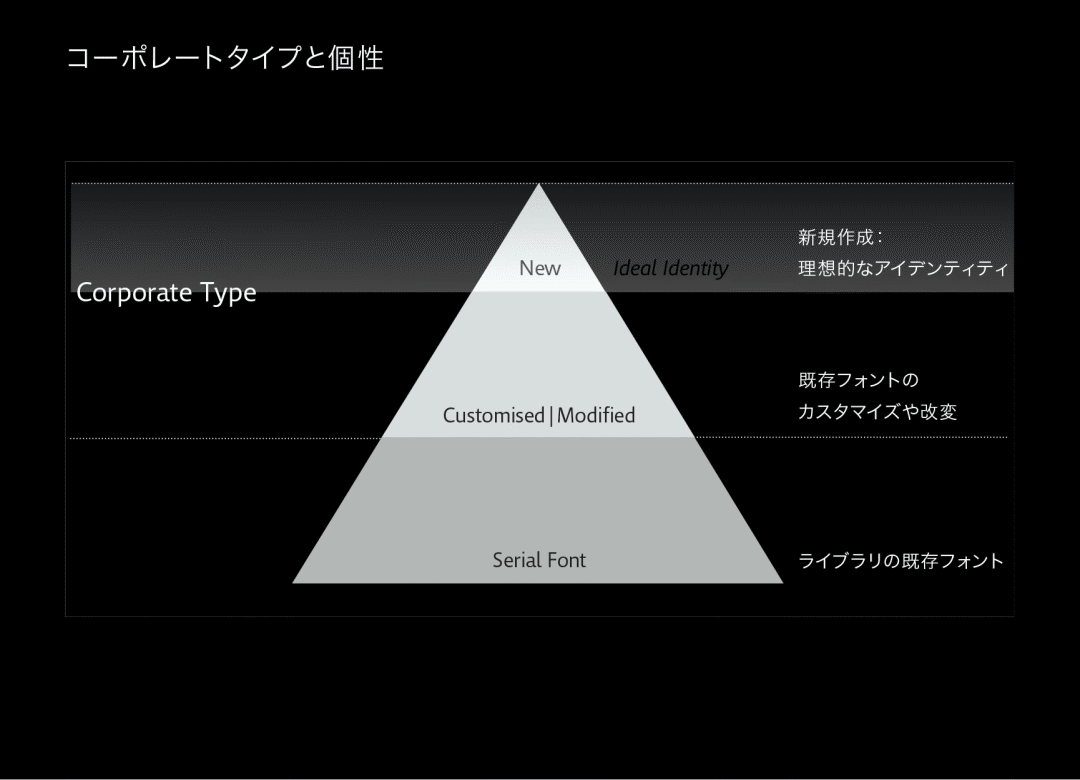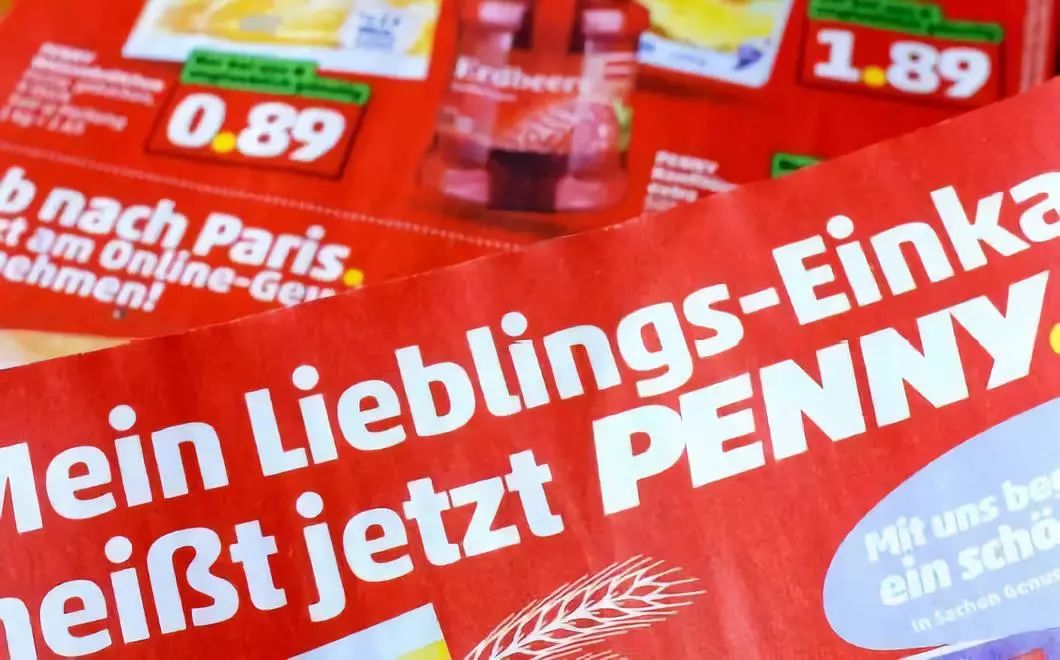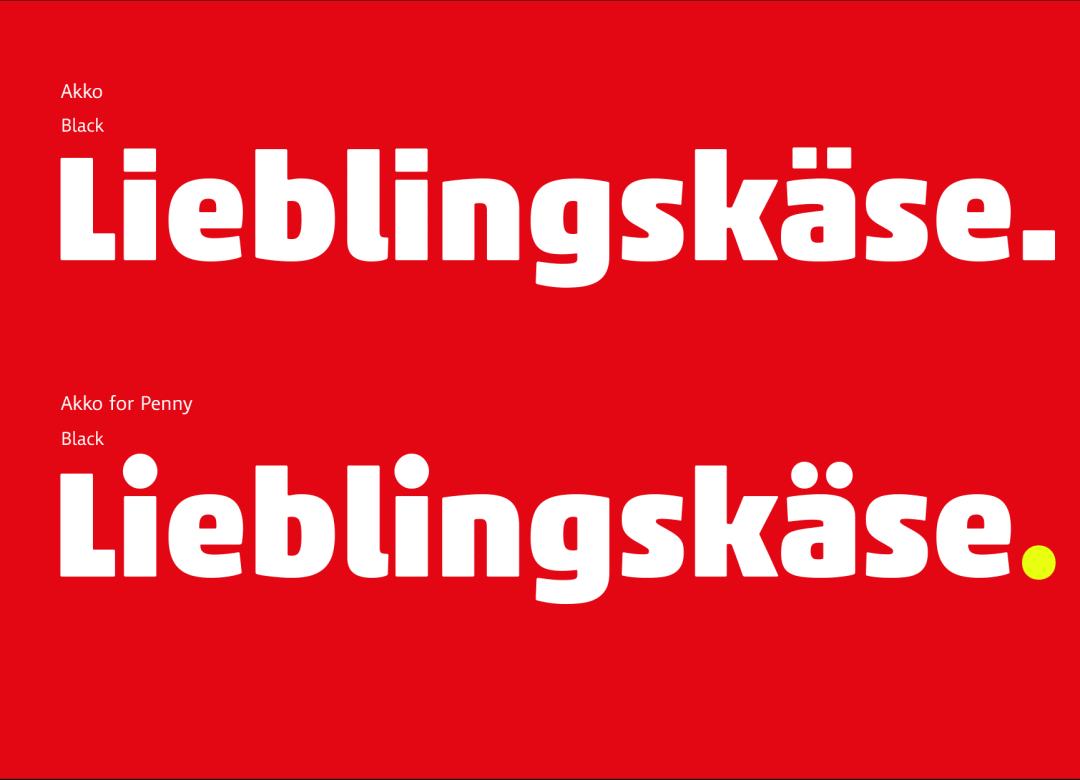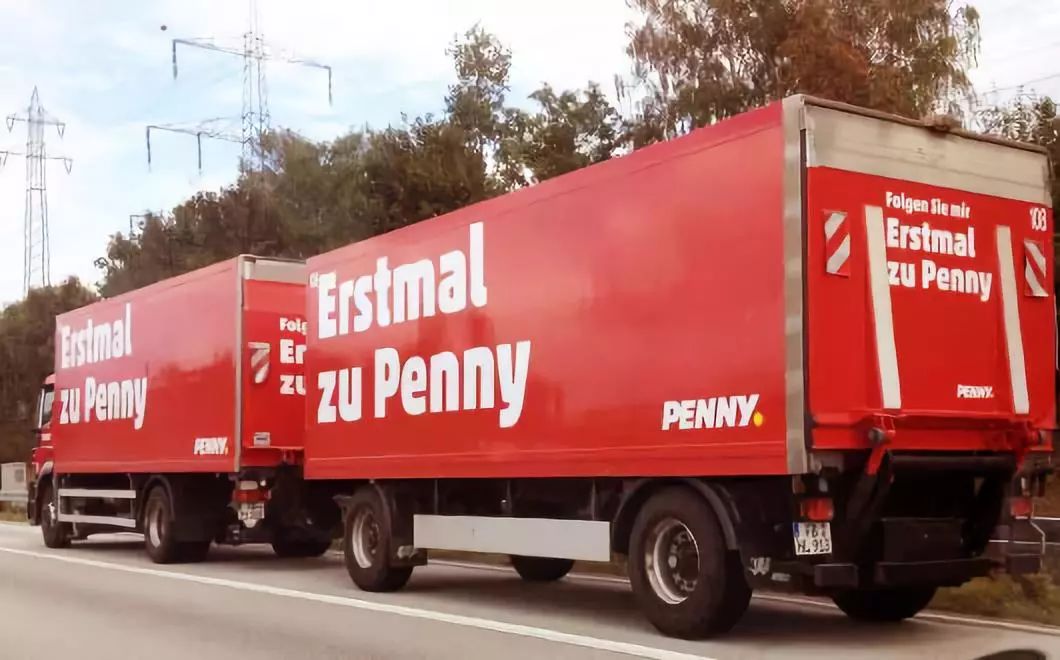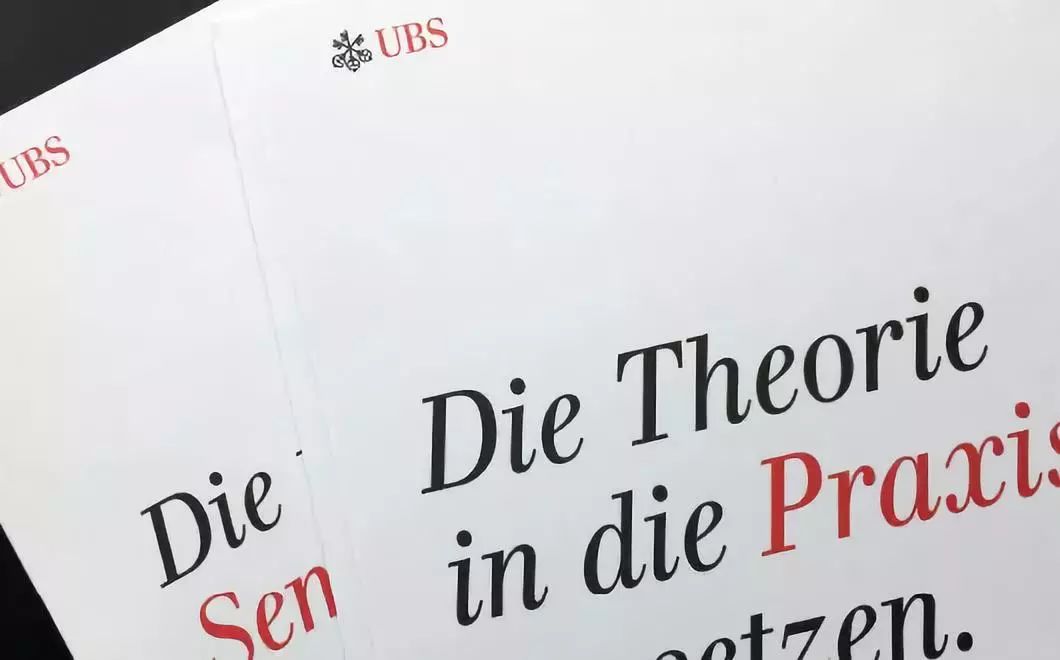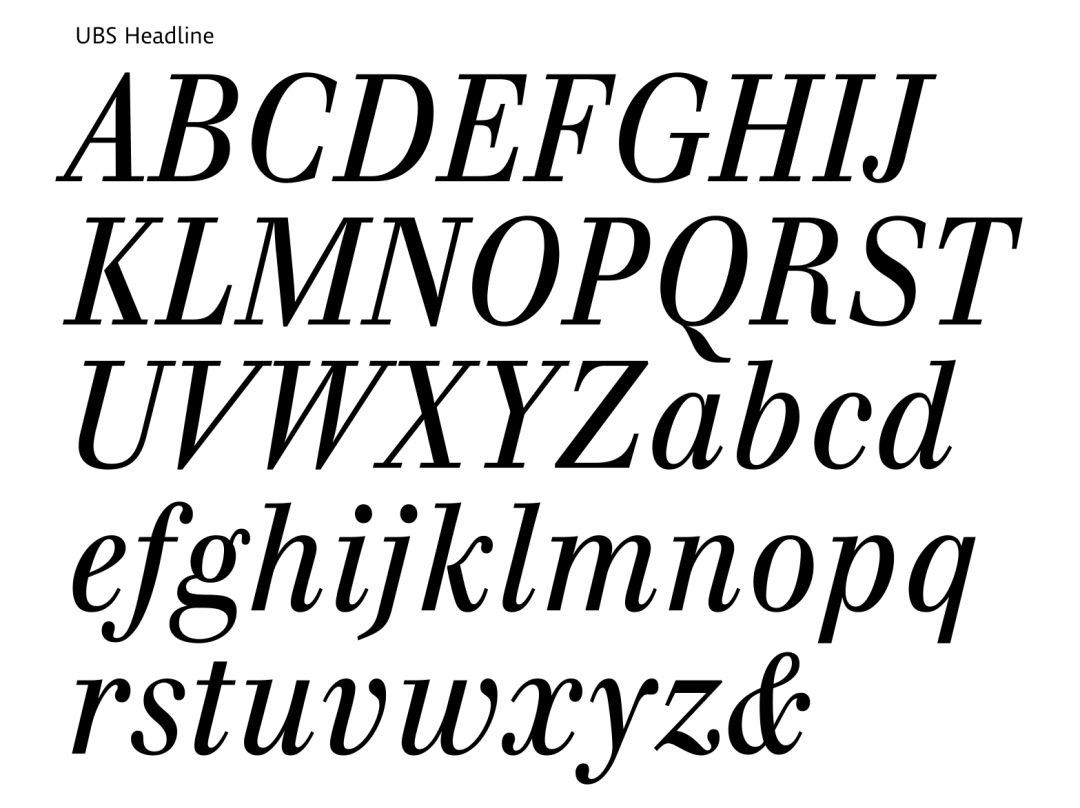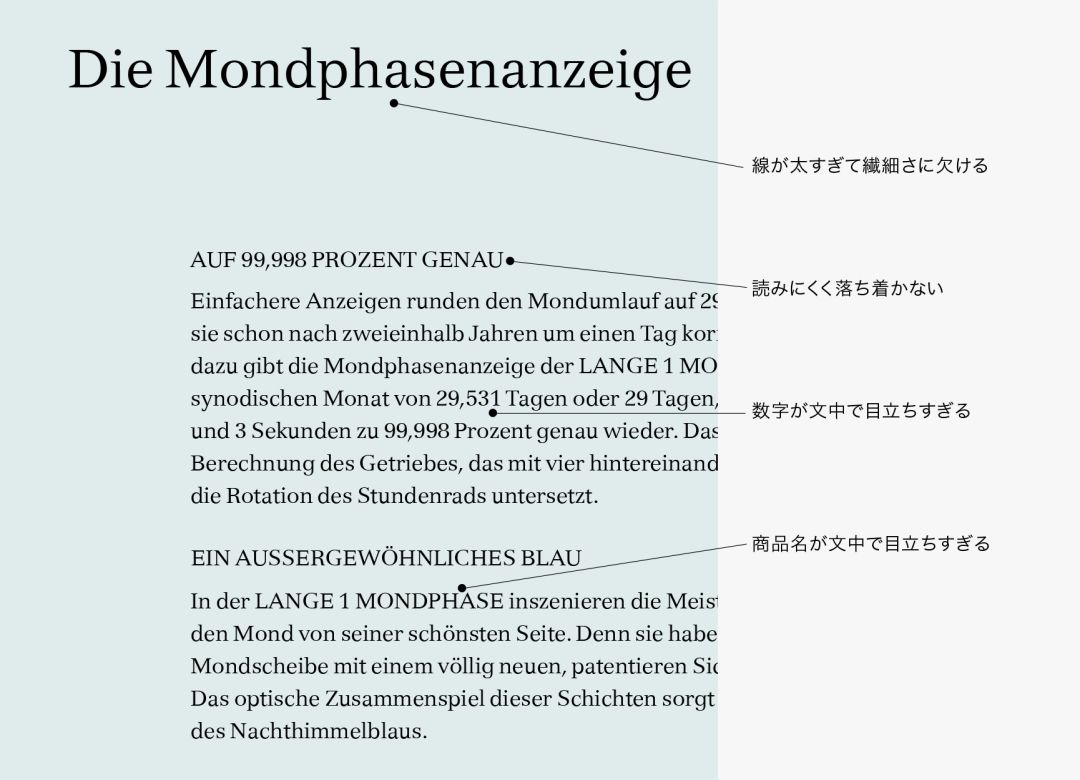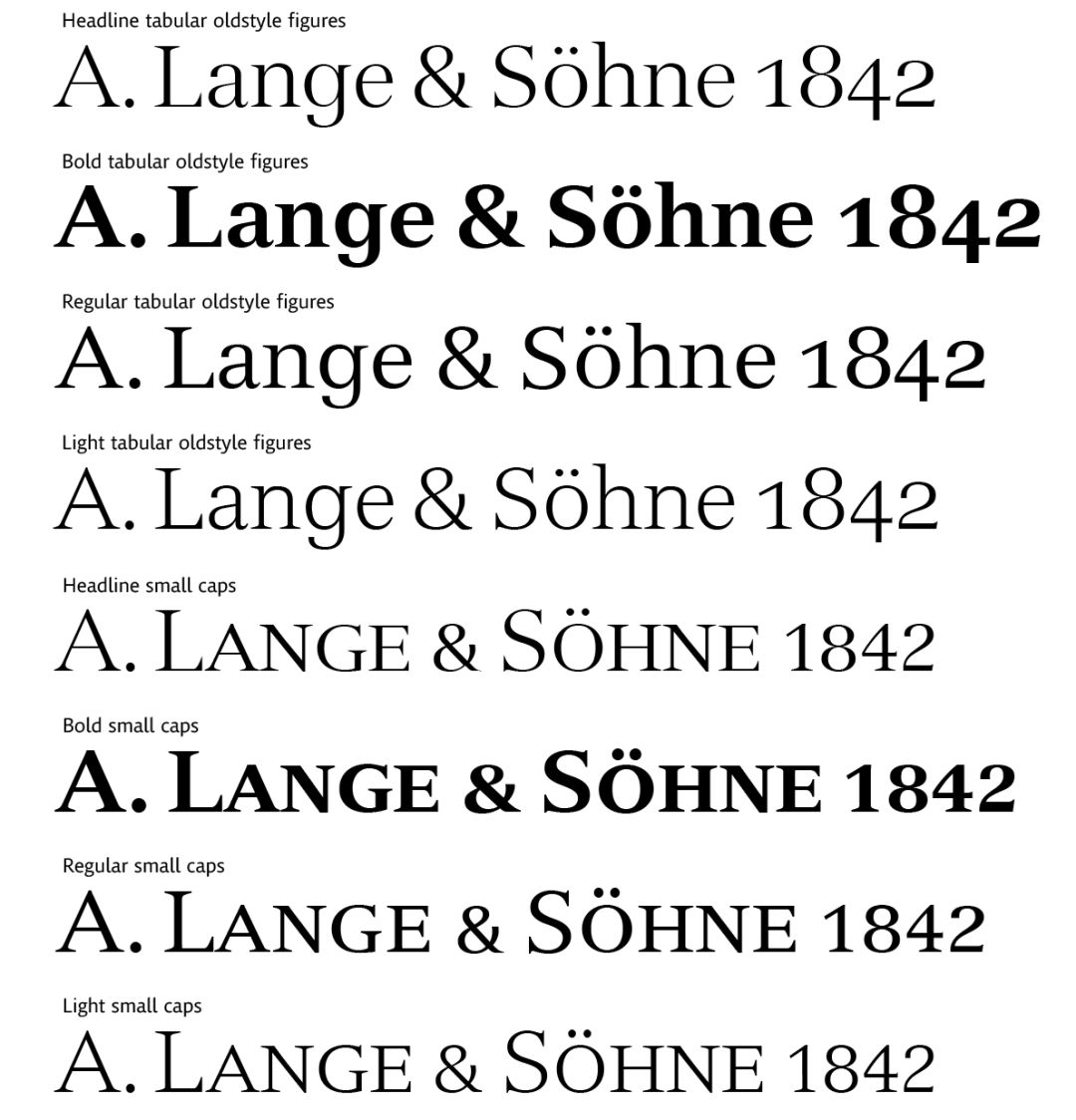
日本NDCX小林章|一场字体与品牌的对话
小林 章|访谈活动
Moji Design Conversation Vol.1
树立品牌的形象
在拥有130年历史的德国Monotype公司,小林章先生担任字体设计总监(Type Director)。从字体设计的制作方向到新字体的企划立项、企业专用定制字体的提案及制作,负责范围广泛的业务。2017年10月12日,我们邀请到小林先生,就字体设计和文字进行了一场访谈活动。活动的前半部分将通过多个案例直击企业字体的制作现场。
企业字体与个性
山口(NDC)
首先,请您谈谈在进行企业字体的开发和提案时都有什么建议。
小林章
开发主要有3种方法。最基础的方法是从金字塔※最底层的程序库现有字体中选择。从Monotype现有的大约3万字的欧文字体中,选出符合形象的字体直接使用。但是,挑选的这些字体有可能别人也在使用,不能算是独一无二的企业字体。相反,为了突出品牌的独创性,还有金字塔顶端的全新制作的方法,从零开始创作草图。采用这种方式,可以设计出独一无二的理想字体,但也存在耗费时间和成本的不利之处。因此,可以考虑采用金字塔中间位置的定制和改良(modified)的方法。从现有字体中挑选字体,并在此基础上进行改良,既确保了字体的个性,又无需耗费时间即可制作出企业字体。
演绎繁华气质−Akko for Penny
小林章
我与品牌代理合作,为德国大型连锁超市Penny制作了企业字体。对我制作的Akko字体进行改良,形成了Akko for Penny。要说哪里不同的话,配合Penny标识的标志性黄色圆点,应该为点的地方全部设计成了圆形。具体来说,就是把小写字母“i”和“j”、德语中的重音等符号全部设计成圆形,把最后的圆点设计成黄色。分为4种粗细,有普通的无衬线字体(Sans-serif)和一种在日本称作圆角Gothic的“Rounded”字体共2种类型,根据需要分别使用。
我是2001年来的德国,总觉得当时的Penny有些寂寥,是个去了以后会没有精神的地方。而现在,只要去了那里,就能感到更有精神了。我觉得这就是Akko字体运用得当而带来的好结果吧。
符合行业需求的现代化−UBS Headline
小林章
接下来谈的是为瑞士UBS银行开发企业字体的故事。我们对Monotype现有的一种Walbaum字体进行了改良。Walbaum是基于1800年左右的金属活字而设计的传统字体,文字具有独特的均衡感,个性非常鲜明。虽然想要突出传统特色,但作为银行来说,要是不突显现代感就会给人一种不佳的印象。因此,我们对部分文字进行了改良,使之更加具有现代感。这就是UBS Headline字体。
将左右填满,调整纵长,设计成具有现代感的文字。并且,将无衬线字体(Sans-serif)略微加粗,使之在网站上也能使用。数字和倾斜字体(italic type)也减少了个性特征,更加突出现代感。
同样以倾斜字体(italic type)为基础的Walbaum字体,对于用于装饰的小写字母“k”等进行了调整。“z”这类字符倒是一定程度上保留了传统感,但并不会产生繁杂感吧。在保留高档和传统的一面的同时,UBS Headline突出现代感的目的也得到了确保。
富有恬静感的设计—Versailles for ALS
小林章
我还参与了将基地设在德国的高档钟表制造商A. Lange & Söhne公司的产品目录字体开发工作。那是以Versailles为基础字体开发的Versailles for ALS字体。从“l”和“g”就能轻易分辨出来,将上下略微加长,突出了高雅气质。
字体家族构成一共4种,包括Versailles和标题字体。我让数字也具有多种形态,补充制作了Old-style数字和Small Caps。
请看产品目录的排版页面。怎么样,这种寂静感。单是看到这种稳重感,就能传递出腕表的高档感和传统感,还有产品的精密感。那么,为了展现封面的静谧感,都使用了多少种字体呢?
标题,小标题,还有正文。由于是钟表制造商,所以在正文中会出现大量的数字。还会出现产品名称。为了展现这种复杂的结构、组合方式,客户提出了各式各样的需求。
用一种字体来表现所有需求怎么样?那么刚才所说的静谧感就无法体现了。标题线条太粗的话,会缺乏细腻感,小标题要是用了大写字母,就会太拥挤,不够稳重。要是数字的高度跟大写字母一样的话,就实在太显眼了。为了解决这些问题,使封面保持静谧感,我用多种字体进行了组合。
只选择必需的
小林章
欧洲品牌代理的特点是在下单阶段就开始设想使用时的情景。另外,还要了解现有字体中哪种与客户需求最接近,通过调整,字体形象会发生改变。还要考虑到必要的变化种类和形象气质的演绎。例如,就像最初的Akko for Penny,可以分开使用不同粗细程度来展现一种繁华气质,还有像Versailles for ALS那样,设计出带有静谧感的字体的案例。其中的共同点就是区分使用了3~4种不同字体。在数字方面,要是在正文中不使用Small Caps,就会显得太突出,要是用了Old-style数字又会太显眼,知道了这种情况后,才提出了上述需求。因为已经了解了使用方法,所以定制字体的家族构成也就定下来了。我们并不是盲目制作,而是从一开始就只考虑必要的需求。
日本与欧洲的区别
山口(NDC)
日本的企业是如何引进企业字体的?
小林章
在日本,很多客户会提出“希望能做出这种感觉来”的要求。“那么这种字体怎么样?”我们一般会从提出几种建议方案开始。与日本的企业打交道时,比较有意思的是以客户给出的大体形象为基础,反复进行提案和选择。这样比较花时间,但是企业的理念和理想形象逐渐变得清晰,这一点很有意思。
小林 章访谈活动
Moji Design Conversation Vol.2
ブランドの声をつくる
在活动的后半部分,通过日本设计中心(以下简称“NDC”)内部提出的问题,我们将从常见文字的“创作”角度出发进行回顾。
追求易辨识性 — Tazugane Gothic
加藤(NDC)
您认为在已有的字体中哪种字体较为完美?
小林章
Monotype公司首次制作的日语字体,Tazugane Gothic。可以用于正文,而我认为也可以用于广告牌等。因为其中采用了在字母中由于辨识性良好而广为人知的Neue Frutiger。如果我们从远处观察对比Frutiger和Helvetica,可以发现Helvetica有些零碎。因为这种良好的辨识性,Frutiger被各国的交通系统采用。在日本,如果观察机场和广告牌使用的字体,可以发现框体饱满的字体设计成为了一种标准。到目前为止大家都认为这是理所当然的,但真的是这样吗?像Frutiger这样易于辨识的字体逐渐受到更多人的青睐,日语也逐渐开始改变框体饱满的设计。顺应这样的时代趋势制作而成的正是Tazugane Gothic。作为正统的字体,我认为不应强调气氛,而是考虑字体怎样才真正易于辨识。
上:Helvetica Bold|下:Frutiger Bold
便于制作、还是可读性强?
小林章
在日本,约从2011年开始,高速公路引导标识的文字变为Hiragino Kaku Gothic。标识中使用的“京”字实际上有2种,照片右侧是东京的“京”。其原因在于中央的四角部分和东京(“東京”)的“東”字对齐。设计要项中注明了东京用这种,京都的“京”用另一种。但是逐渐会混淆,也有使用左侧字体的例子。这取决于制作方的选择。以前用反光带手工制作文字时,我认为与“東”在口的高度上对齐的右侧的“京”较容易操作。但是因为有两种“京”,所以会有这样用错的情况。现在随着时代和技术的变化,文字制作已经数字化了,所以我们在设计中能够注重细节。因此,置换为Hiragino Kaku Gothic可以说是一个趋势性的结果,与易于制作相比,人们会选择具有良好外观平衡的字体。易于制作和作为公共广告牌真正具有易读性,完全是两回事。
不考虑媒体的差异
加藤(NDC)
在纸媒上使用的文字和显示在屏幕上的文字是否存在制作上的区分?
小林章
没有根据媒体分别制作文字。如果区分,那么纸媒上是否全部用一样的字体呢?印在光滑的有光纸和印在蓬松质地的纸上是完全不同的,因此我认为不需要区分纸和屏幕。
创作字体需要什么
栗田(NDC)
我想知道创作一种新字体需要多少人力和时间。
小林章
一般来说,无论什么字体,1个人做的话大约需要半年。如果有分工,可能还能稍微缩短时间,但即使有分工,为保持设计的统一感需要花时间进行说明和修改,因此并不是说5个人做就能用5分之1的时间完成。此外,在字体设计中,最初制作的文字会在后来进行回顾和修改,并视其组合进行调整,因此需要时间精力和专注。顺便提一下,Tazugane Gothic的9500字×10种粗细花了约3年时间。
手的重要性和想象力
松田(NDC)
请问在制作现场有哪些东西从过去至今未曾改变,而哪些东西结合时代的变化发生了改变?
小林章
我从事这项工作约30年了,未曾改变的是用手写字。我在写研公司制作日语字体的时候,文字的曲线部分是用细描笔手描写成的。我认为只有经过长期的手写训练,才能切实理解手的动作,在任何场景中都能划出美丽的曲线。谈到结合时代的变化,有一点是做出的文字交付印制的时间。在照片排版的时代要等上2个月左右,现在使用打印机只需要约0.7秒。我们有一项确认工作,要观察自己做出的文字在其他尺寸下的排版效果,现在这项工作变得更快了,起到了非常大的帮助。不过,字体设计师有些特殊的能力,制作字体时已经在设想实际用于多大的尺寸。我认为优秀的字体设计师能想象到自己设计的文字在1~2mm下使用时的观看效果。既需要经验,也需要想象力。
字体设计中的“笑谈”
佐佐木(NDC)
我想知道有否有只在字体设计师之间流传的玩笑。
土井(Monotype)
刚才谈到如果全部用大写字母排版,会显得繁杂,如果对方发来的电邮全部使用大写字母排版,会感觉对方似乎在发怒。所以我们之间谈到过,如果感到烦了,就全部用大写字母回复(笑)。
让世界更温柔
井上/植松(NDC)
至今,哪种字体让您感觉最新鲜?
小林章
我最喜欢的字体是Cooper Black。如果说有什么好,就是看起来不聪明(笑)。我上高中的时候,在美术部做海报时选了这个字体。喜欢艺术字以来,我一直手写这种字体。Cooper Black源于美国芝加哥手写招牌工匠的书写风格,看起来略轻浮,实际上相当有底蕴。越看越有感觉。那么温柔,感觉在微笑。例如,如果世界各地政治家说的话都用这种字体打出来,我想世界会变得更柔软一些。我希望载有禁止信息的标识牌能尽量使用这种字体。那样的话,这个世界应该会变得更宜居一些。例如这个标识是我合成的,实际上并不存在,但我希望变成这种风格。
消除自己的风格